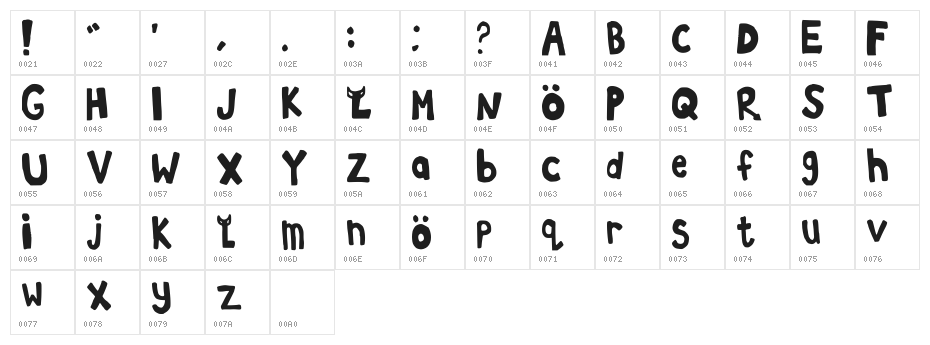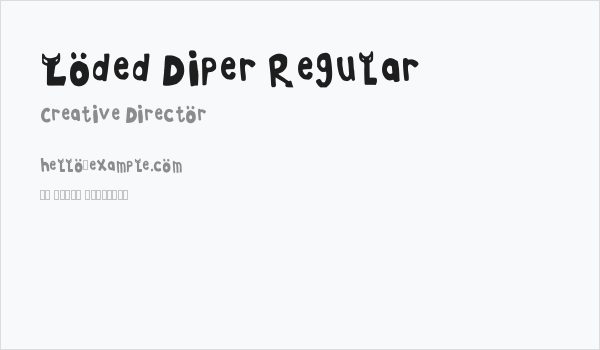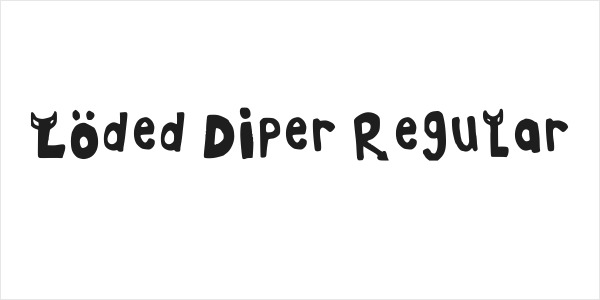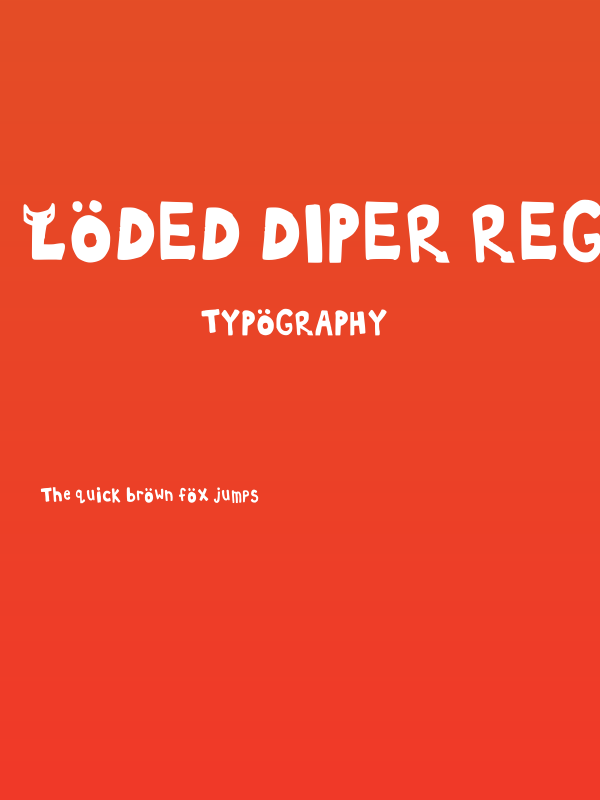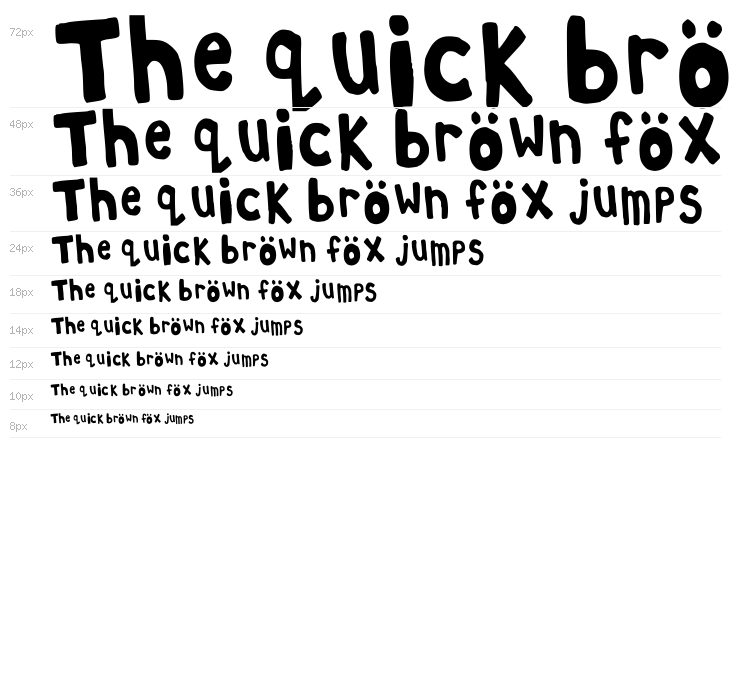
Loded Diper Regular Font
| Общий стиль | Playful, Whimsical |
| Область применения | Headlines, Posters, Branding |
| Рекомендуемые проекты | Ideal for children's book covers, comic strips, playful branding, and event posters. |